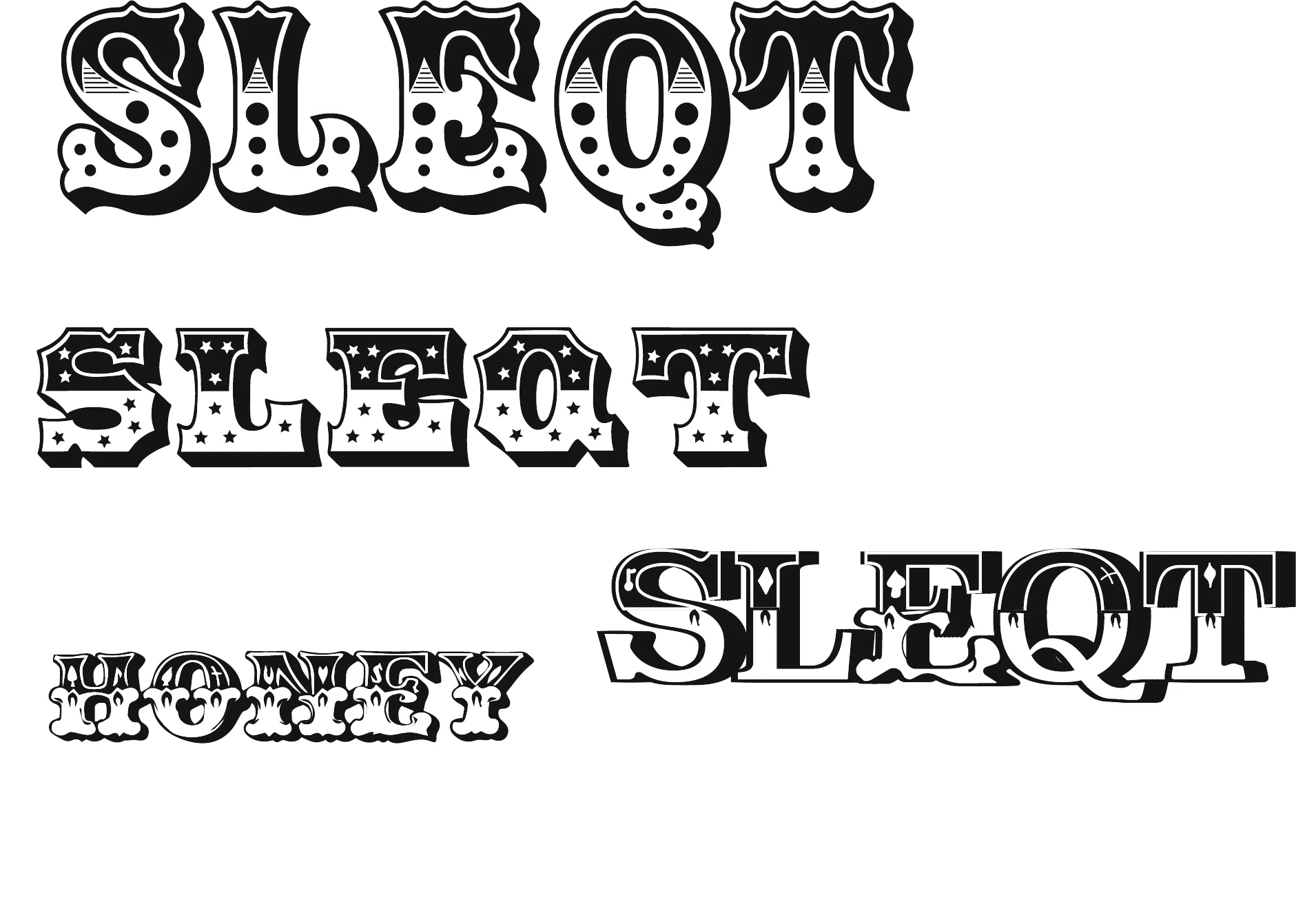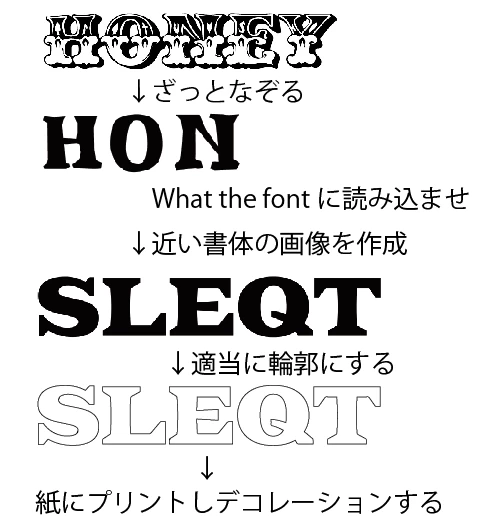
フォントの作り方について
画像にあります「HONEY」を参考に、同じようなフォントで「SLEQT」と言う文字を作成したいです。
ヒラギノゴシックフォントからはじめ、自分で作成しているものが右下の「SLEQT」の文字になります。
Illustratorにはたくさんのフォントがあり、似たようなものなら上の2つの「SLEQT」のように作ることもできました。
しかし、全く同じフォントはもちろん見つからず、みなさまならどのように作成しますでしょうか?
ひたすらアンカーを追加し、ダイレクト選択ツールでパスを変形させたものが「SLEQT」の「E」の文字です。
答えを行ってしまえばそのフォントはAdobeの「Zebrawood」ですね。
bizarre_nさんが説明されているAdobe Fontsにありますので、CC契約していれば使えますよ。
膨大なフォント群から書体を探すのは、Photoshopのマッチフォント機能を使うと便利です。
ごめんなさい逆でしたね、すいません。
こういうロゴタイプは一度手書きで書いたものをスキャンしてトレースした方が早いと思います。
1.参考にしている「HONEY」をざっとなぞってみる
2.なぞり書きしたものに、似ているフォントを"What the font"を使って探す。
3.What the fontで書きたい文字である「SLEQT」の書体を探し画像にする
4.適当に輪郭を作成し、プリントアウトする
5.自分の描きたいデザインをデコレーションしていく
この手順なら手描きの工程まで、効率よくサクサクと進められそうです‼︎
あとは、わたし自身の手描きのスキルだけになります。笑
フォントを作るということですが、いろいろと用語等に混乱が見られるようですので、ちょっと確かめさせて下さい。
・文字の形のデザインをされたいのでしょうか?でしたらそれは「フォントを作る」というより「レタリング」ということになります。これには近道とかは特になく、自分で一からデザインを起こして、ひたすら書いていくということになります。
・「Illustratorにはたくさんのフォントがあり」ということですが、Illustratorにあるのではなく、Adobe CCのサービスの中に、色々なフォントを使用できるAdobe Fontsというサービスが含まれているのです。
それ以外にも国内、国外を問わず様々な会社からフォントは発売されています。あなたがデザインを借りてきている文字も、そういった会社から販売されているフォントの一つかもしれません。
フォントでなかった場合は、レタリングデザインということになりますね。そのデザインには誰か作者がいるはずですが、その作者さんはデザインを借りることについてOKしてくれているのでしょうか。
・ご自分のデザインで作った文字の字形を「フォント」というプログラムにして、OS上で使えるようにするためには、Illustratorではできません。フォント作成のためのアプリケーションが必要です。Glyphsというアプリケーションが有名ですが、他にもいろいろあります。
フォントとして成立させるためには、形をつくる上で色々制約があります(線幅は使えず、全て塗りにしなければならないなど)
文章力が乏しく、わたしの意向をうまく伝えられていませんでした。
フォントを作りたいわけではなく「HONEY」のデザインを参考に「SLEQT」と言う文字を作りたいです。
返信内容にありますとおり、わたしがしたいのは「文字の形をデザイン(レタリング)」でございます。
ひたすらに1から、自分で描いていくしかないのですね。
どこかに裏技的なものがあると、期待しておりました。
様がこのデザインを作るとしたら、どのような工程で作られますでしょうか?
わたしが思いつくのは
白紙の紙にペンでデザインを描く→写真を撮ってIllustratorのアートボードに配置する→画像をトレースする→
ペンツールや消しゴムツールを使って、デザインを整える
です。
Illustrator初心者で、思いつくアイデアが少なく、ぜひ知識を共有していただけると嬉しいです。
レタリングに限らず、「ある形を作るにはどうしたらよいか」ということになると思うのですが、特に特別なことは考えつきません。
作りたい形を手書きなりなんなりでラフスケッチし、それをどうしたら効率よく形にできるか、Illustratorの機能を考慮しながら詰将棋のように考え、実際に手を動かしていくという感じになるかと思います。
もちろん、前提として「Illustratorの機能を一通り知っている」ということになりますから、勉強は常に欠かせません。バージョンが上がると機能も変化し、追加されていくものです。
同じ見た目でも、Illustratorの初期の頃(自分が使い出したのは1992年ごろです)と現在とでは、手順がかなり違ってきていることも多いです。ペンツールを使ったベジェ曲線の書き方は変わりませんが…
作りたい形によって「詰将棋」の手順も変わります。常に有効な「裏技」が存在しないことはそのことからもお分かりかと思います。
一通りチュートリアルを勉強するなどして、知識の引き出しを多く持つように心がけるとよいのではないでしょうか。